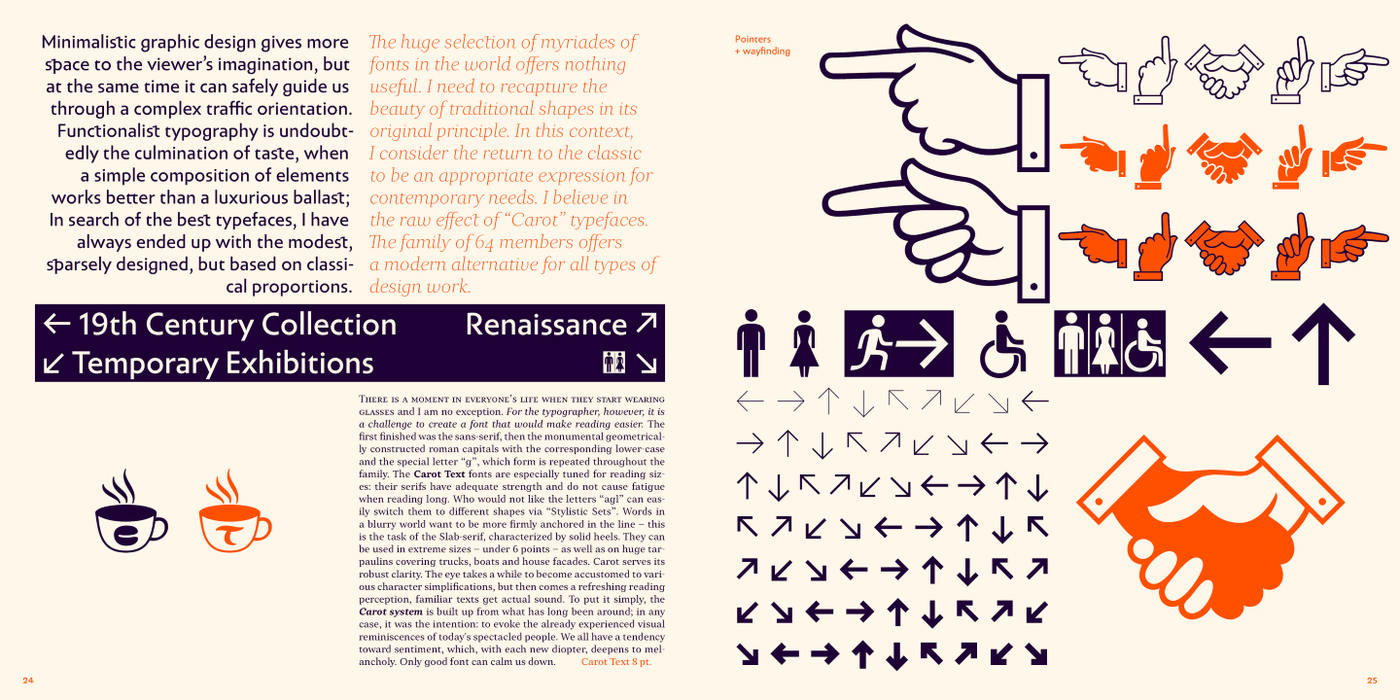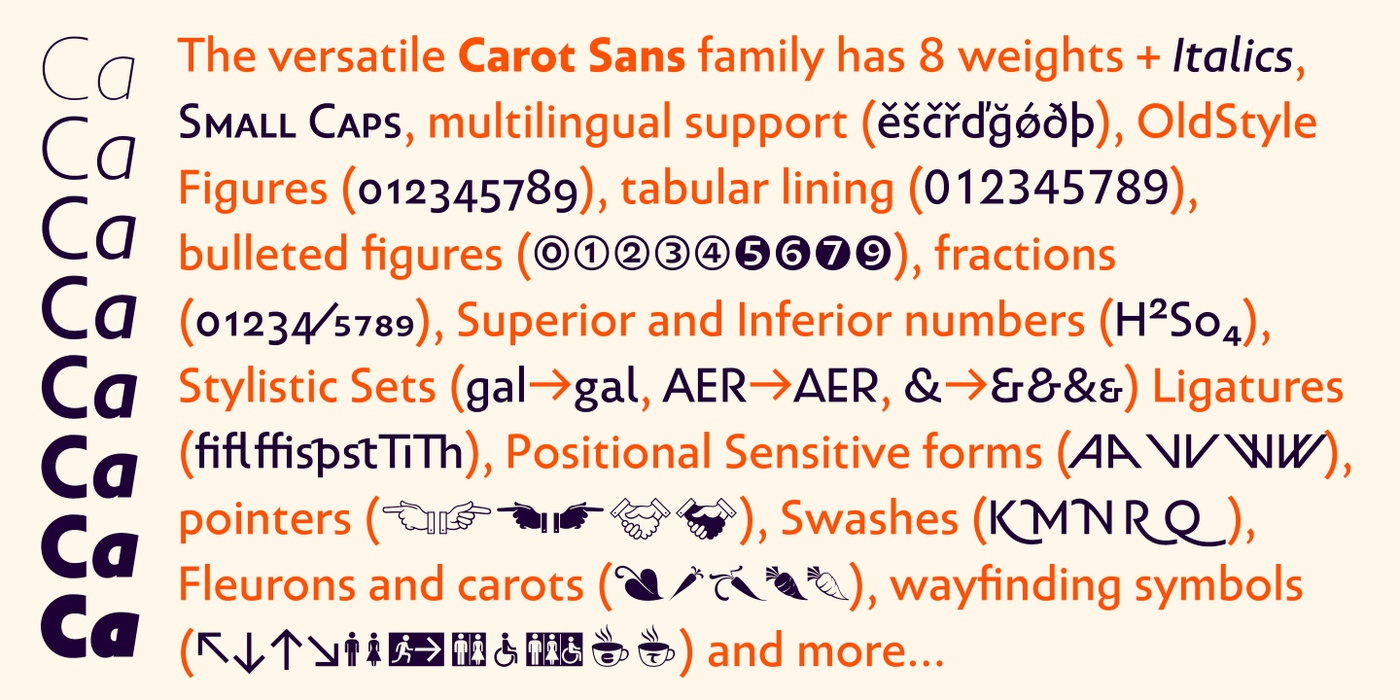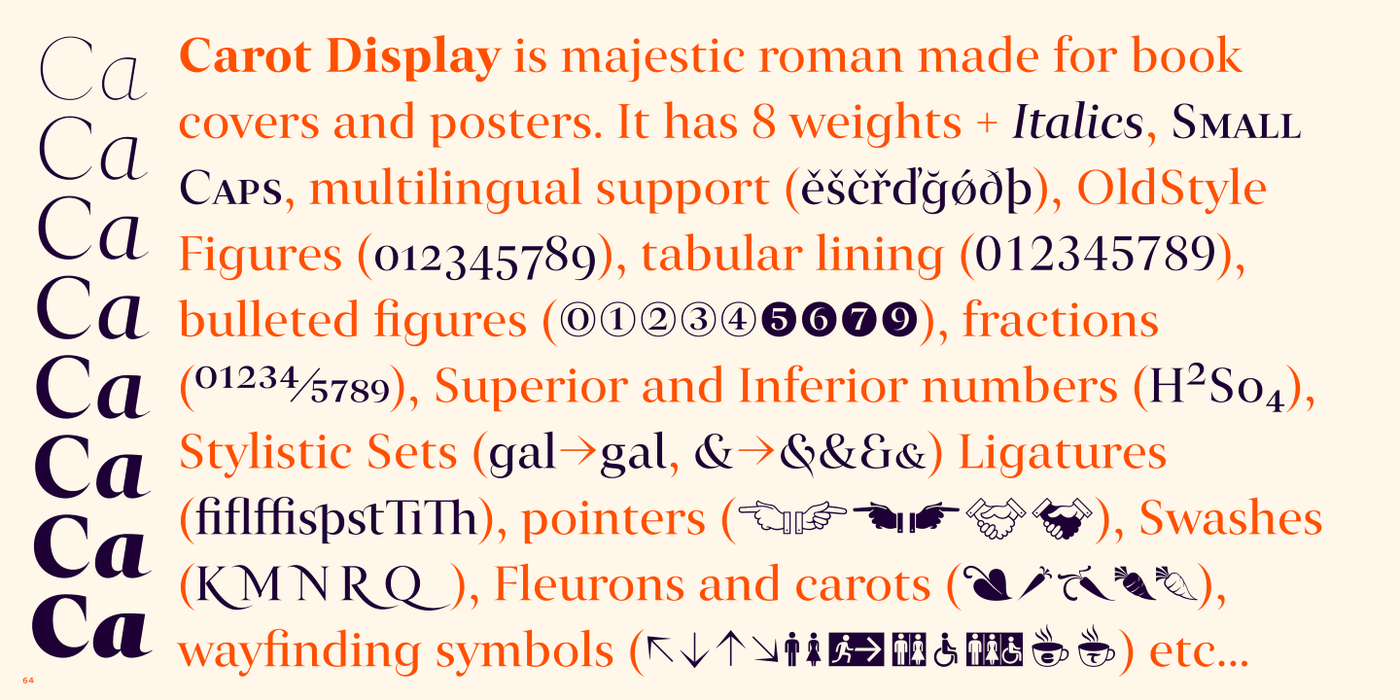
Pfeile und zeigende Finger - Welche digitale Schrift enthält das?
Gerade bin ich auf der Suche nach schönen Pfeilen in Stilen des 19. und frühen 20. Jh.
Pfeile und zum Beispiel Hände mit zeigenden Fingern, wie man sie aus alten Werbeanzeigen in Zeitungen kennt.
Kennt jemand eine digitale Schrift, die solche Zeichen in guter, schöner Ausführung enthält? Eine Kostenlose Schrift wär super, da ich erst mal nur ein, zwei Zeichen benötige.
Gibts noch weitere Vorschläge? Vielleicht doch was kostenloses?
Vor kurzem erschienen – nicht gerade kostenlos, aber sehr ansehnlich und neben einigem anderen auch mit diversen hübschen Manicules ausgestattet: Carot
Die Carot Symbole sind nicht so ganz was ich suche. Zu schlicht, zu geometrisch, zu einfach. Aber ich denke, bei einer der oben genannten Schriften werde ich fündig. Auch das Video von Ralf ist sehr hilfreich.
An alle die´s Interessiert - hier steht noch mehr über ☞ Manicules:
Wobei mir erlaubt sei, auf zwei zentrale Fehler in dem Text hinzuweisen:
• Das englische Wort manicule kommt von lat. manicula, nicht -lum.
• In Attavantis Buch zeigt das Alinea () eine neue Rubrik (also ein Rechtsthema) an und der Index () Sinnabschnitte (capitula) innerhalb derselben, wie man im letzten Beispielbild des Artikels sehr schön sehen kann – sie differenzieren aber nicht, wie im Artikel behauptet wird, Rechtsfragen von Kommentaren. Die beiden Zeichen fungieren hier also als Gliederungszeichen, keineswegs als Symbole. Anstelle des Index verwendet man heute im kanonischen Recht übrigens das Paragraphenzeichen (§).